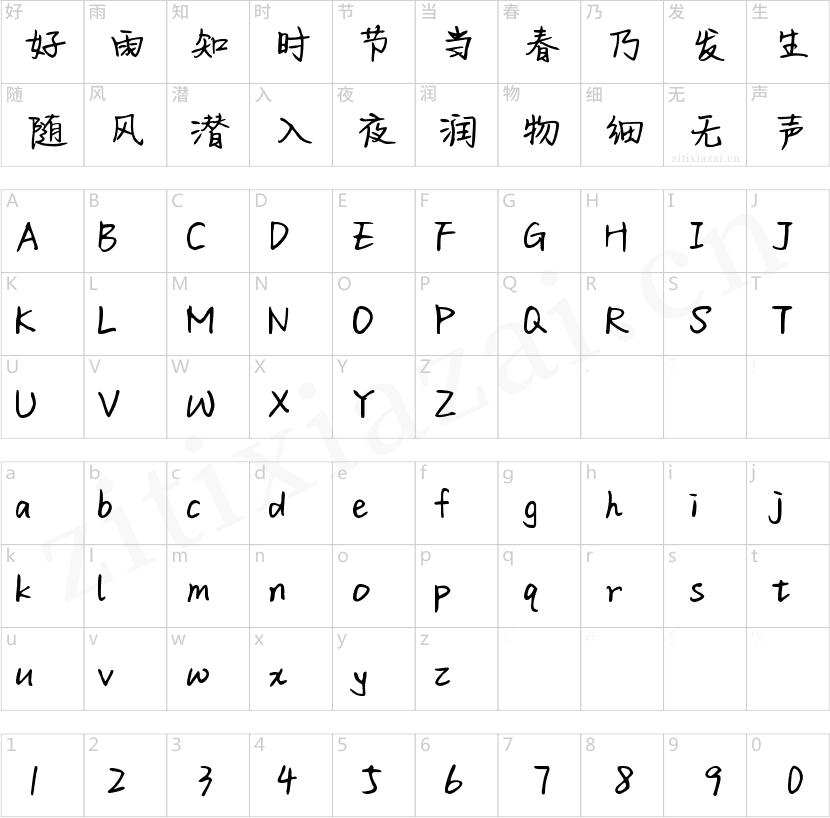
Aa恋恋樱落
Aa恋恋樱落,这款字体结构工整、笔画清晰,兼顾美观与易读性,适用于标题、正文、海报、包装、LOGO 等多种场景。字形优雅稳定,风格百搭耐看,适配日常排版与创意设计,让文字呈现更舒适、更具质感。Aa恋恋樱落一笔一画,皆是细节,以均衡的比例、流畅的线条打造舒适视觉体验,字形端正大气,风格简约现代。无论是商业设计、品牌宣传还是日常排版,都能轻松驾驭,让文字更有格调与力量。Aa恋恋樱落字体下载。
Aa恋恋樱落是一款非常具有艺术性的字体,它的设计灵感来源于对古典艺术的研究,同时又融入了现代字体设计的元素。字形优美,笔画粗细变化自然,给人以大气、典雅的感觉。Aa恋恋樱落是一款既传统又现代的字体,它的设计充满艺术感,美观大方,实用性也非常强。无论是对于设计师还是对于普通读者来说,都是一种非常不错的字体选择。Aa恋恋樱落适合用于具有艺术感的场合,比如海报、宣传单张、书籍封面等。由于其字形流畅且具有动态感,也适合用于大量的文本排版,如报纸、杂志等。